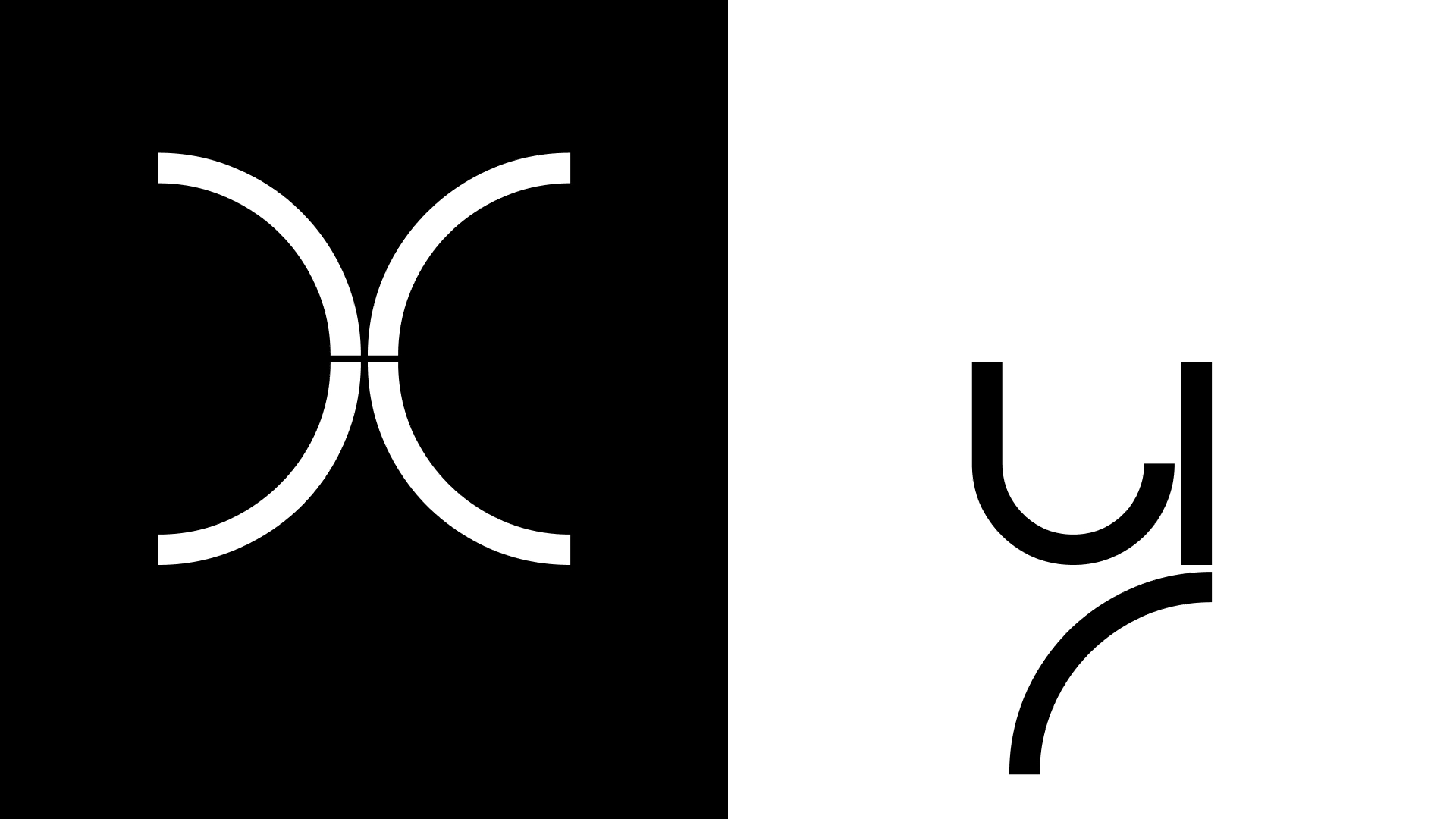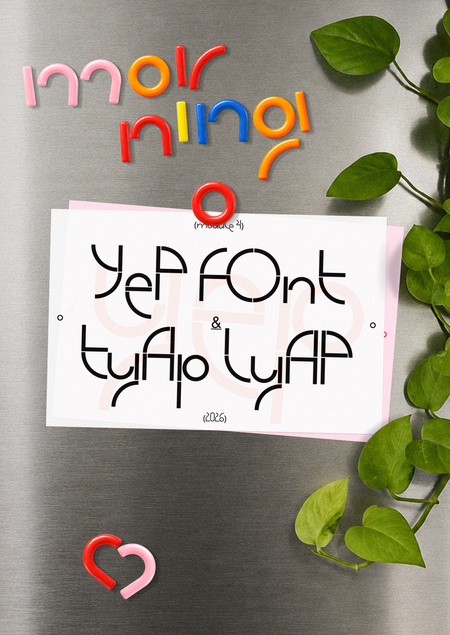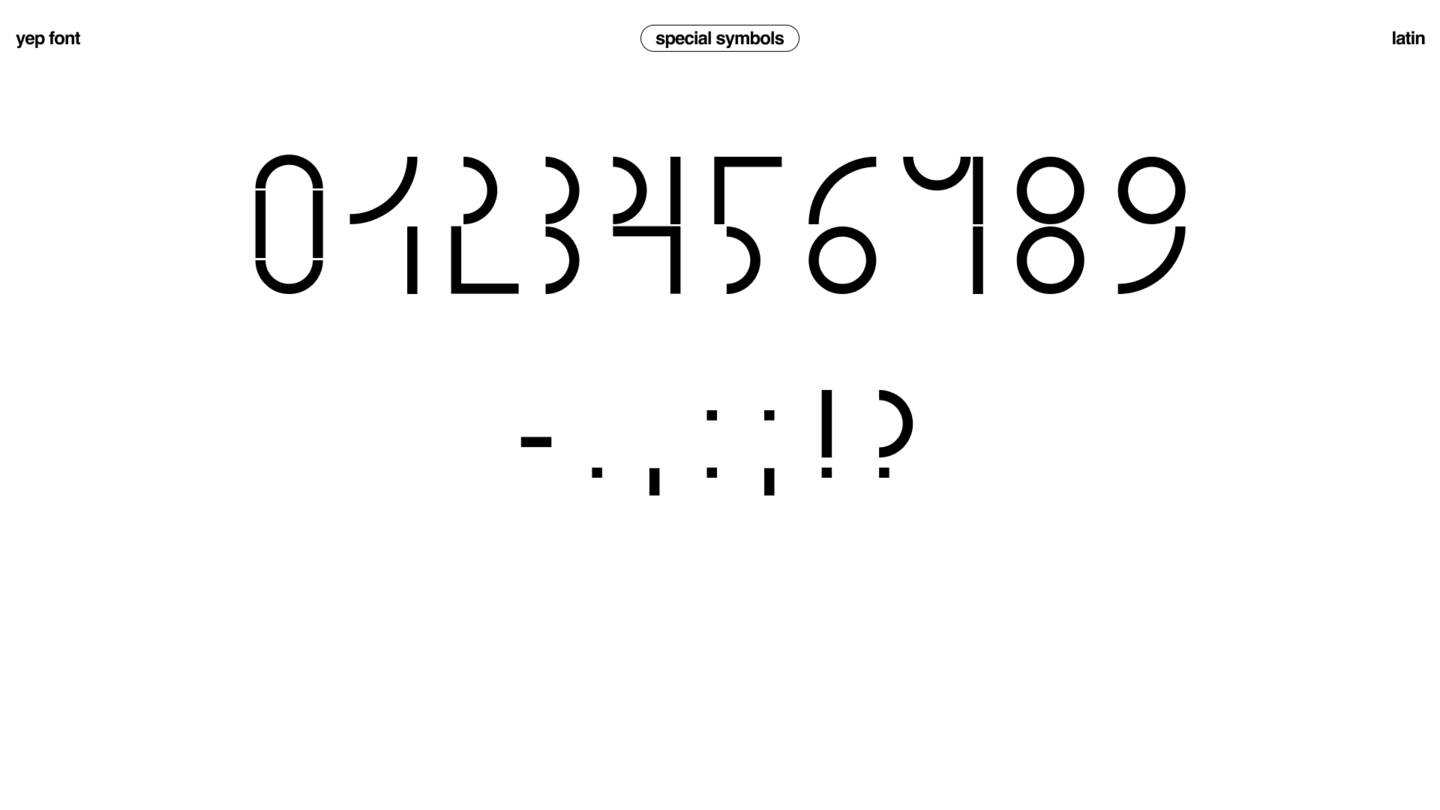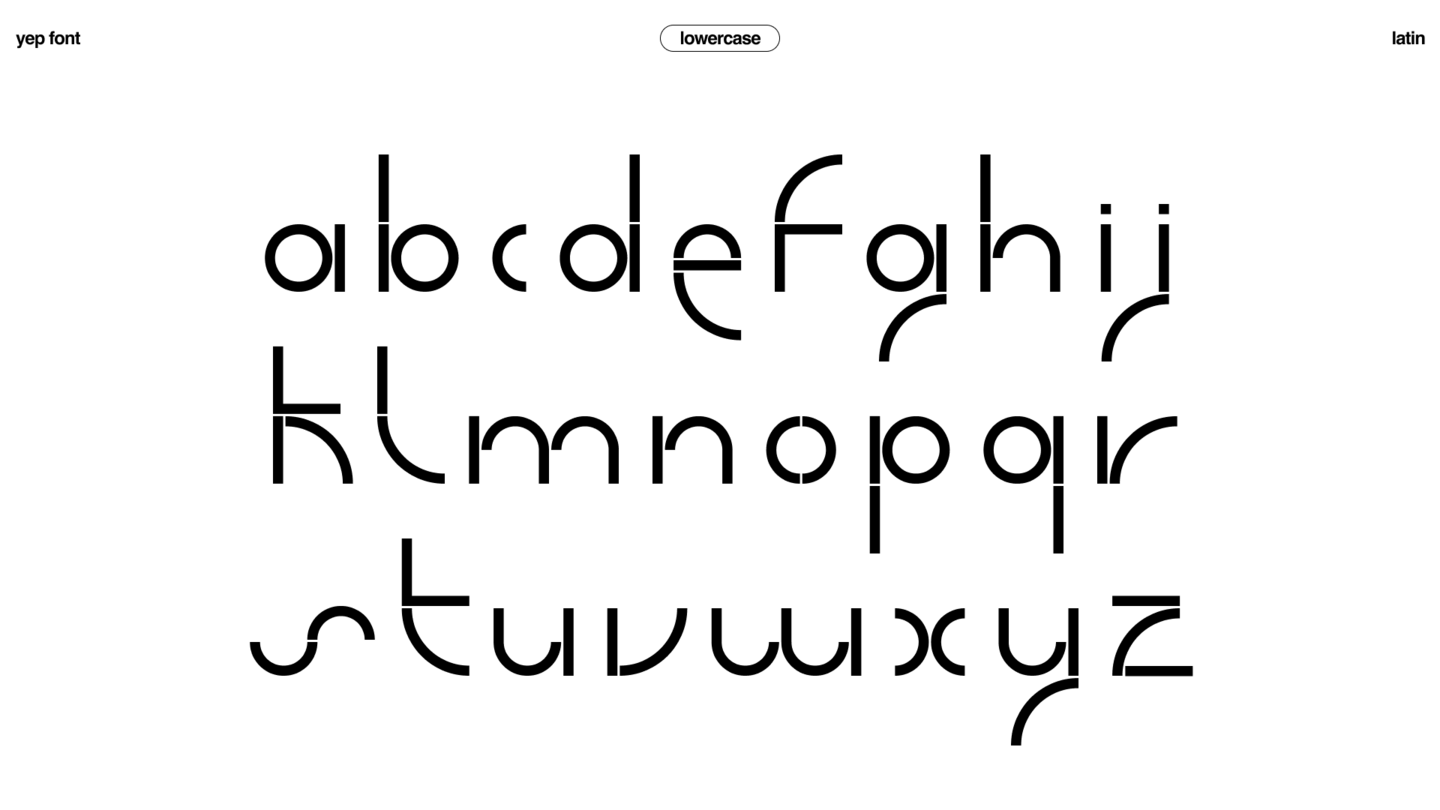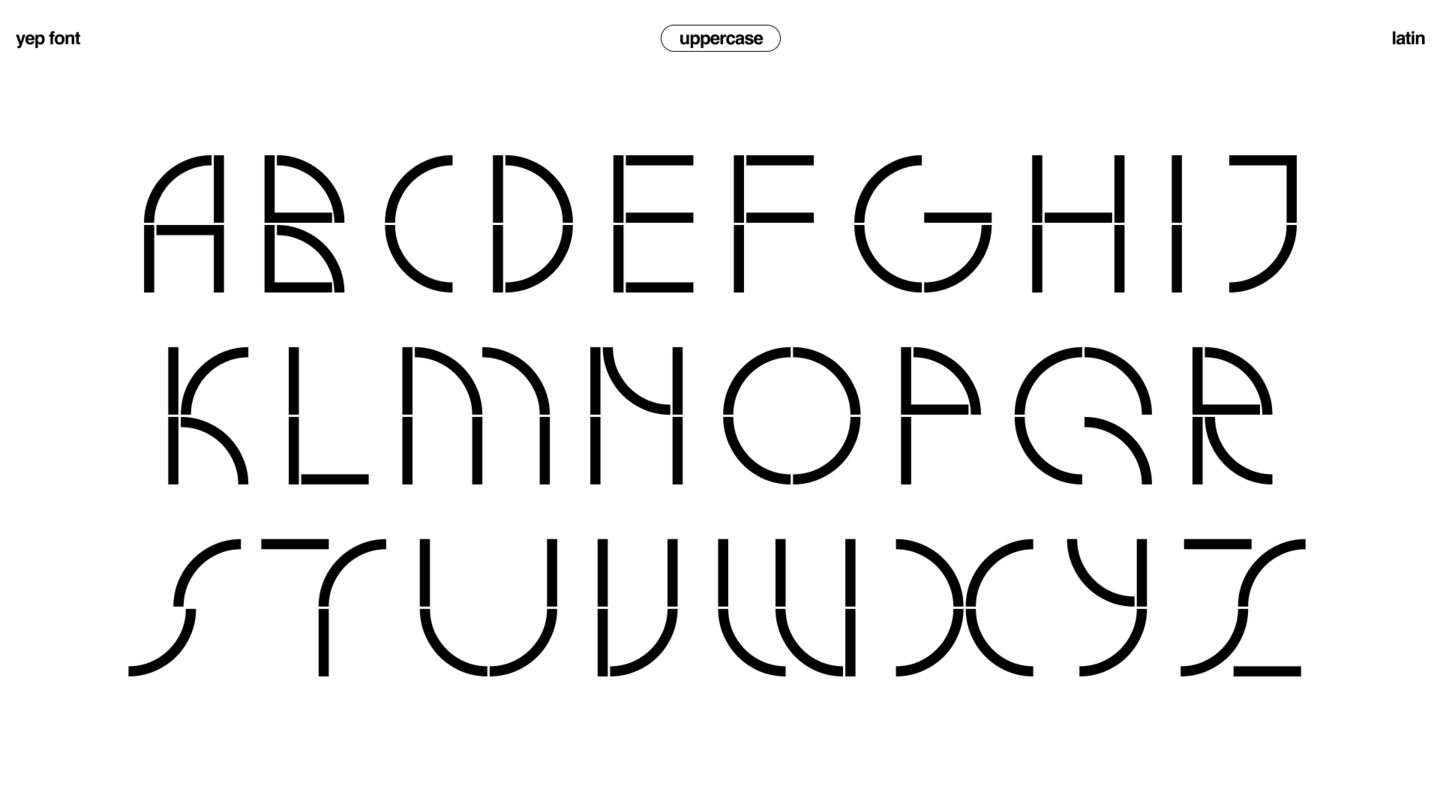
Yep font — модульный акцидентный шрифт, собранный из 6 базовых модулей
Магнитный буквенный конструктор Tyap Lyap — набор магнитных модулей, из которых можно самостоятельно собирать буквы,
слова и собственные вариации шрифта